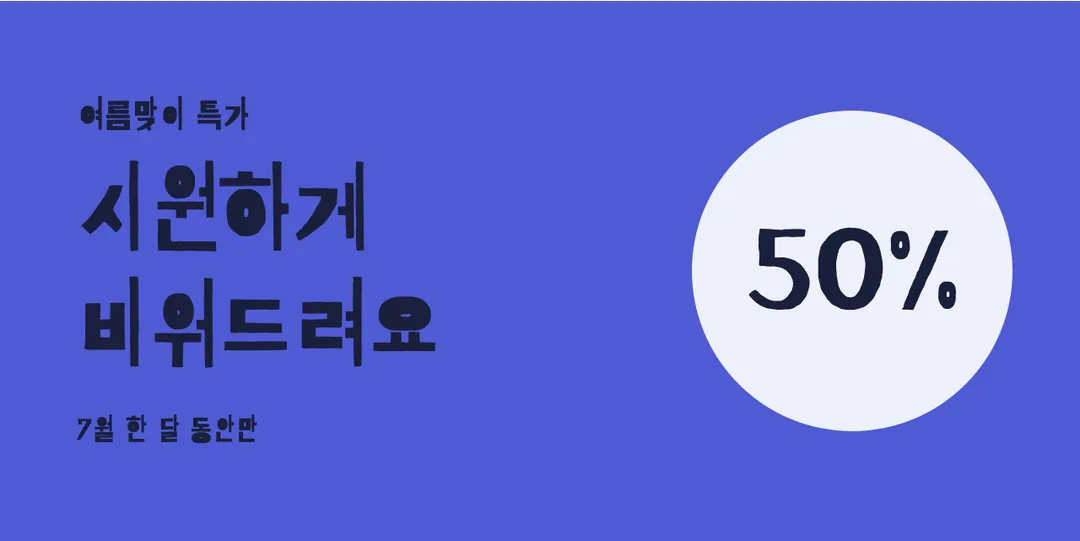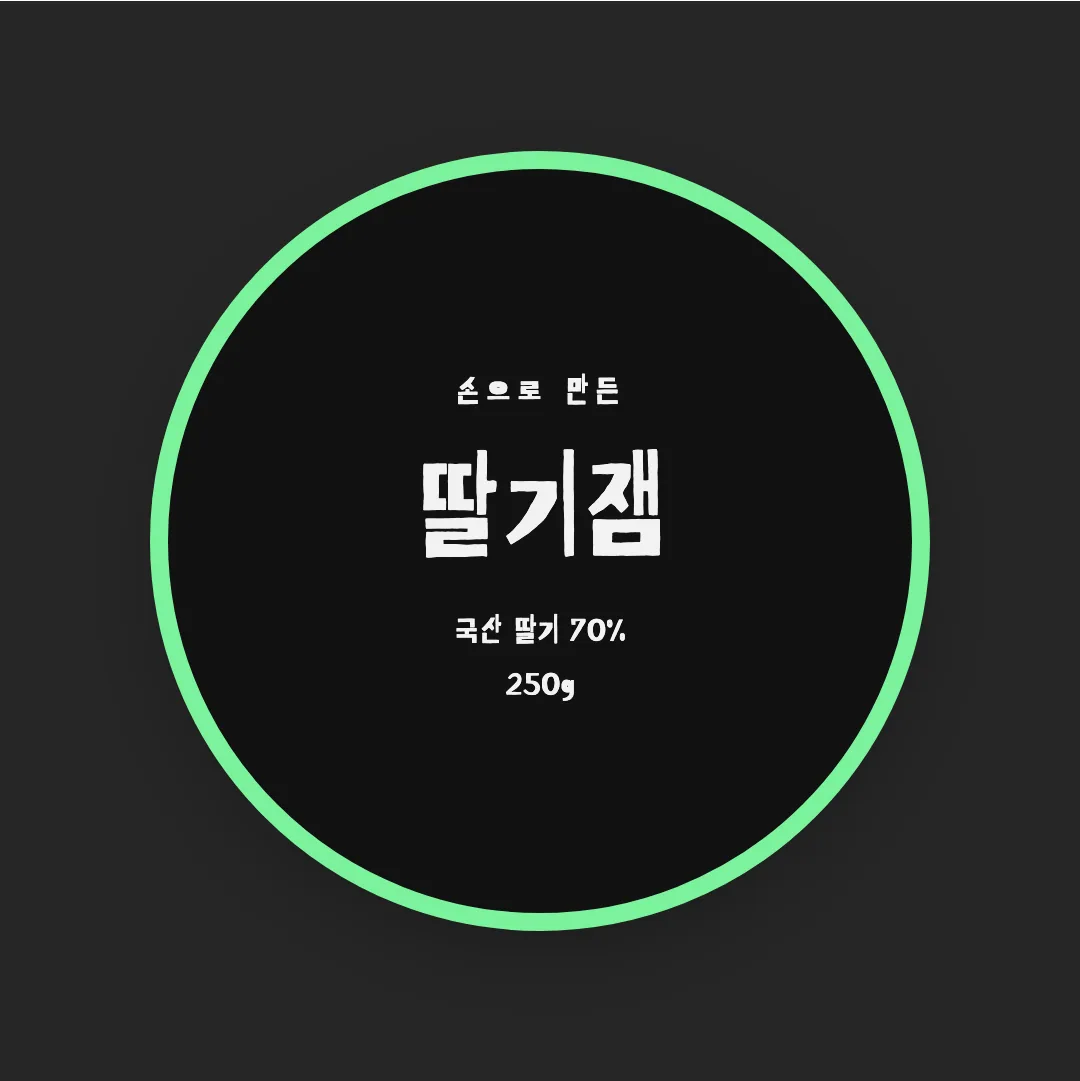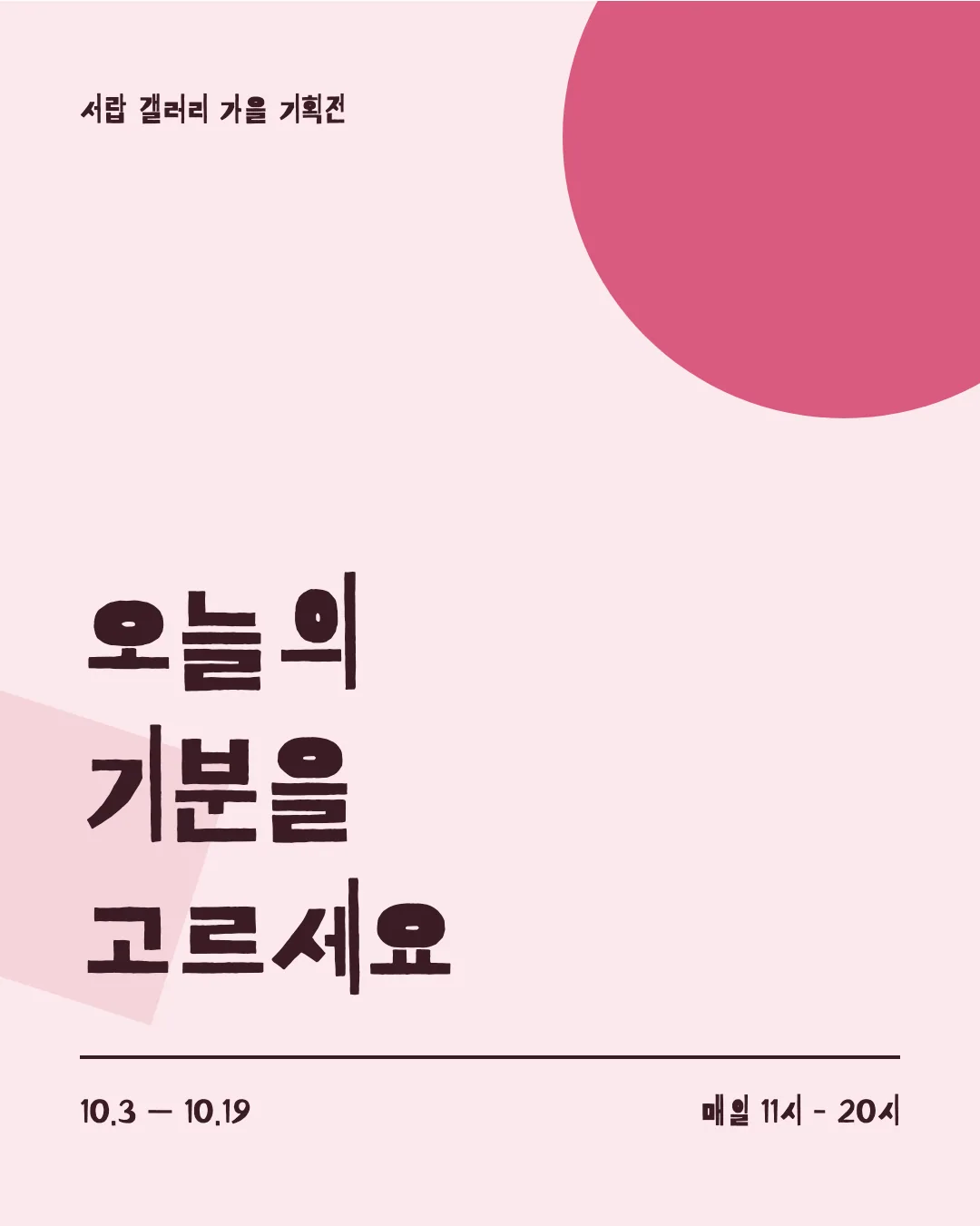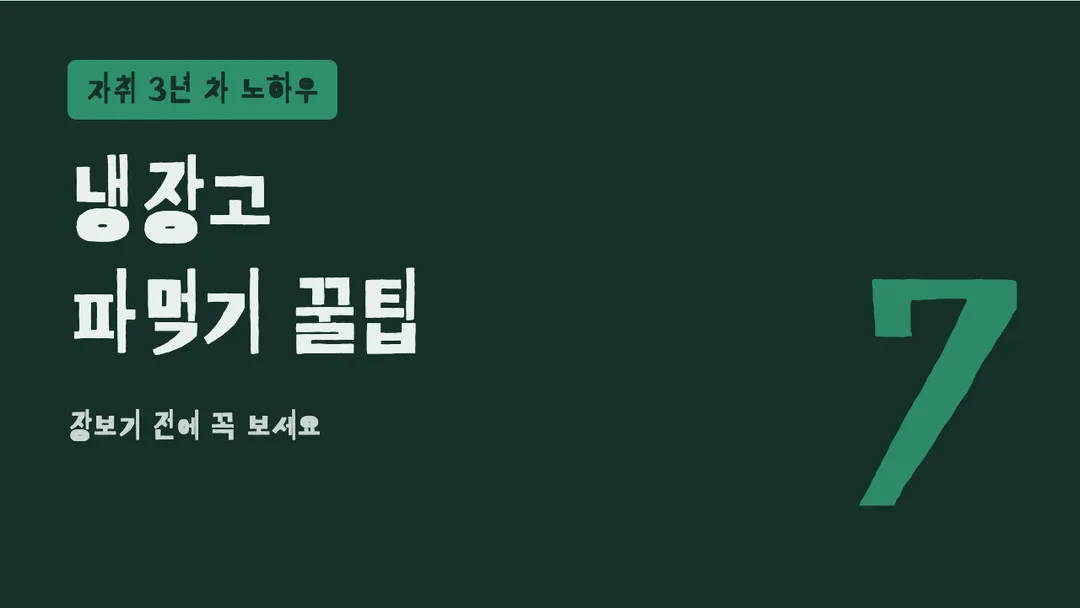
손맛이 강하게 드러나는 개성 있는 장식체입니다. 짧고 인상적인 문구 한 줄에 포인트로 쓰기 좋습니다.
배달의민족 기랑해랑은 우아한형제들 (Woowahan Brothers)의 무료 장식체 폰트예요. 인쇄·웹사이트·포장지·영상·임베딩·BI/CI에 상업적으로 무료 사용할 수 있어요.
배달의민족 기랑해랑로 직접 만들어 본 디자인 예시예요. 이미지를 누르면 크게 볼 수 있어요.